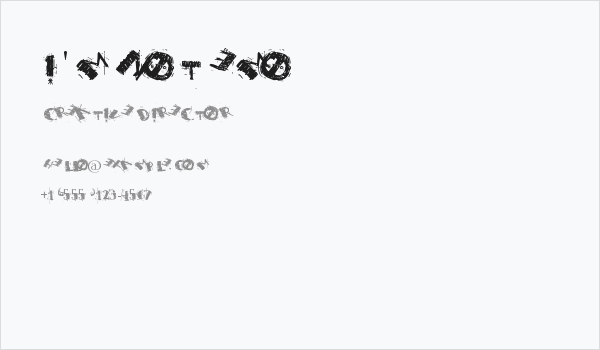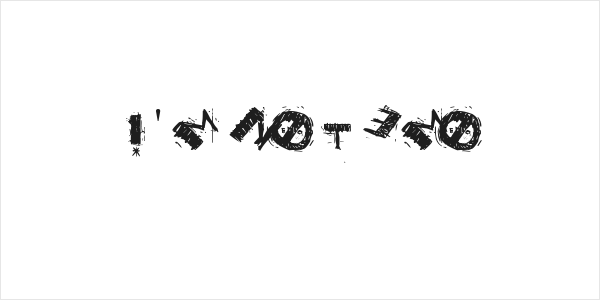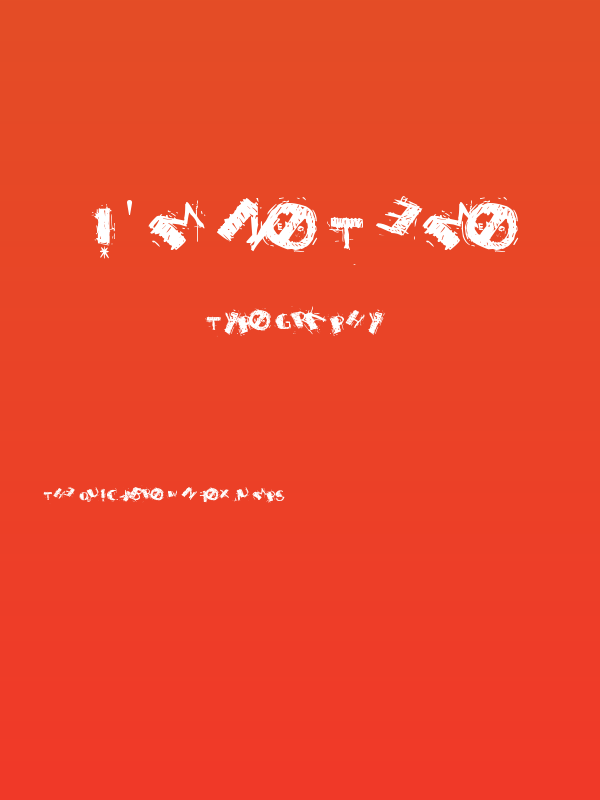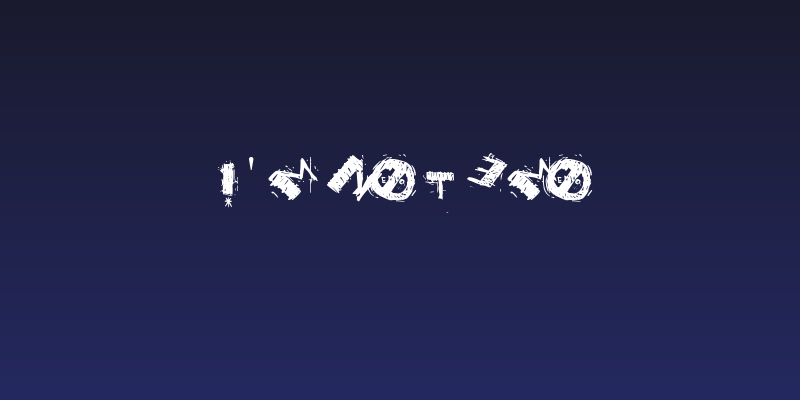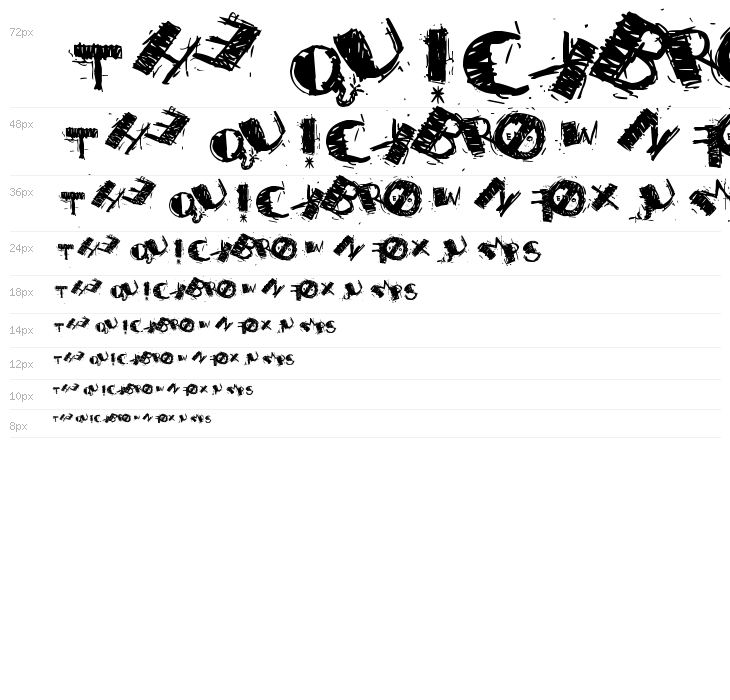
I'M NOT EMO Font
| Stile generale | Grunge, Edgy, Rebellious |
| Progetti proposti | Album covers, posters, streetwear branding, skateboarding graphics, and rebellious-themed designs. |